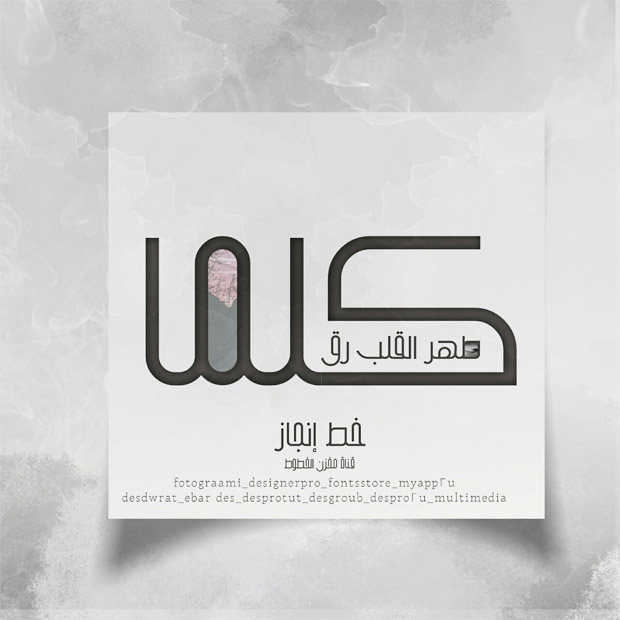
خط إنجاز عربي فني مطور .. خط بأشكال ممدودة إلى الأعلى بطريقة طولية أكثر، وهو مطور من خطوط قديمة، يمكن استخدامه في العناوين والدعاية والإعلان بشكل أكبر، متاح للتحميل المجاني الآن.
خط إنجاز عربي فني مطور